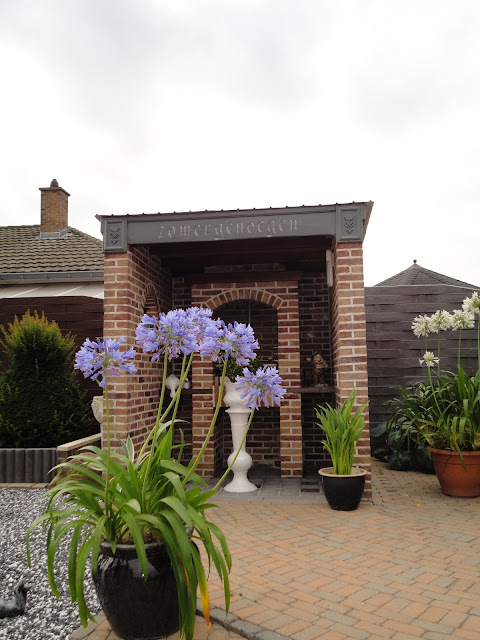
Mijn nicht en haar man vieren feest vandaag !
Niet enkel omdat hun firma dit jaar 10 jaar bestaat, maar ook omdat ze eerder dit jaar in de huwelijksboot stapten.
Dit was mijn kadootje voor hen :
My niece and her husband are celebrating today.
The tenth 'birthday' of their business AND their marriage earlier this year.
This was my present for them:
Ik hield het ontwerp vrij eenvoudig en etste het woord 'geniet' in deze vaas.
Véronique en Gert, geniet van jullie feest en vooral van elkaar !!!!
I kept the design very simple so that the message would speak for itself.
Véronique en Gert, enjoy your party and especially; enjoy one another !!!
Annick
letters in de tuin: deel 2 letters in the garden:part 2
We zijn opnieuw in de tuin van mijn ouders; meer bepaald in de rotstuin, vlak bij de barbecue van vorige blogpost.
Volgens mijn moeder kon dit stukje van de tuin wel wat meer 'cachet' gebruiken , dus beschreef ik nog een steen voor haar verzameling en inderdaad ;een oneven aantal stenen is mooier dan een even aantal.
Today we are in my parents' garden again.
According to my mother, this part of the garden could do with a little something, so I wrote on this white stone to add to her collection . It's prettier now because of the odd number.
Volgens mijn moeder kon dit stukje van de tuin wel wat meer 'cachet' gebruiken , dus beschreef ik nog een steen voor haar verzameling en inderdaad ;een oneven aantal stenen is mooier dan een even aantal.
Today we are in my parents' garden again.
According to my mother, this part of the garden could do with a little something, so I wrote on this white stone to add to her collection . It's prettier now because of the odd number.
letters in de tuin
Toen ik gisteren in de tuin van mijn ouders rondliep, viel me dit woord weer op : "zomergenoegen". Jaren geleden heb ik deze letters getekend en vergroot en nadien heeft onze papa ze dan uitgekerfd in dit hout voor boven de barbecue.
When I was walking in my parents' garden yesterday, I noticed this word again: "summer joy".
Years ago I drew these letters, had them enlarged and my dad carved them into this wood to go on top of their barbecue.
Het grappige is, dat we pas achteraf bemerkt hebben dat 1 letter op z'n kop staat, maar gelukkig valt dat niet erg op. Iemand van jullie die het ziet ?
The funny thing is, that we only noticed a long time after, that 1 letter is upside down....
Do you see which one ?
Een tijdje terug heeft hij ze de letters nog eens terug 'opgefrist' met grijze verf.
Blijft mooi.
Annick
When I was walking in my parents' garden yesterday, I noticed this word again: "summer joy".
Years ago I drew these letters, had them enlarged and my dad carved them into this wood to go on top of their barbecue.
Het grappige is, dat we pas achteraf bemerkt hebben dat 1 letter op z'n kop staat, maar gelukkig valt dat niet erg op. Iemand van jullie die het ziet ?
The funny thing is, that we only noticed a long time after, that 1 letter is upside down....
Do you see which one ?
Een tijdje terug heeft hij ze de letters nog eens terug 'opgefrist' met grijze verf.
Blijft mooi.
Annick
abstract experimentje
| abstract reeksje van drie |
Na drie dagen hittegolf is het nog steeds véél te warm boven in't ateljeeke.
Dus ben ik maar wat beginnen 'spelen' met wat houtjes, een paar kleurtjes bister en wat zwarte inkt.
Een korte wens erbij en klaar.
We've had a heat wave here in Belgium and now it's still too hot in my hobby room.
So I started to fiddle around with some wooden sticks, dentals, a few colours of walnut ink and black ink. These 3 cards were the result of my short play time...
Ben er wel niet 100 % tevreden over, maar kan niet meteen 'identificeren' wat er aan scheelt.
Misschien zijn het de strepen die te breed zijn of had ik misschien andere kleuren moeten nemen ?
Laat het ons maar wijten aan de temperatuur dan.....
I'm not 100 % satisfied with them, but can't tell why exactly.
Maybe the stripes are too broad or perhaps I should have chosen different colours ?
I simply don't know. Let's blame it on the hot weather then,shall we ?
zomerstage kalligrafie in Hoepertingen - summer calligraphy camp in Hoepertingen
| leeg en opgeruimd ateljeeke |
| tidy and clean ! |
Bij het zien van deze foto's, zou je denken dat ik verhuisd ben, want zo proper en leeg is mijn 'ateljeeke' haast nooit !
Maar nee, hoor, veel van mijn materiaal zit hierin, klaar om op kalligrafie-stage te vertrekken, richting Limburg.
| materiaal: klaar om te vertrekken ! |
my material: I'm ready to go !
By looking at the first two pictures, you might think I've moved house, because my hobby space has never been so tidy and clean.
Je 'hoesje' is nu klaar !
Het enige wat nu nog ontbreekt is het kaartje zelf....
Hiervoor neem je dat (effen) kaartje van 9 op 14 cm. Je schrijft je wens erop in kalligrafie-letters of in je eigen handschrift, je maakt nog een gaatje in't kaartje met een koordje erdoor en klaar is kees !
Een leuke én persoonlijke attentie voor iemand én uiteraard zijn er weerd honderden variaties mogelijk....
| 2 verschillende kleuren gebruikt hier |
| of zo kan het ook..... |